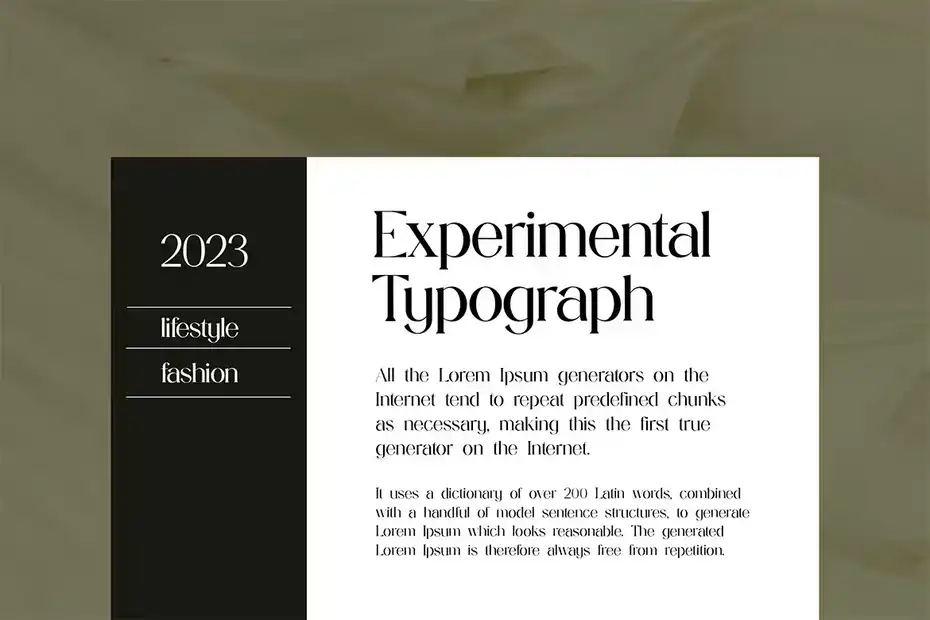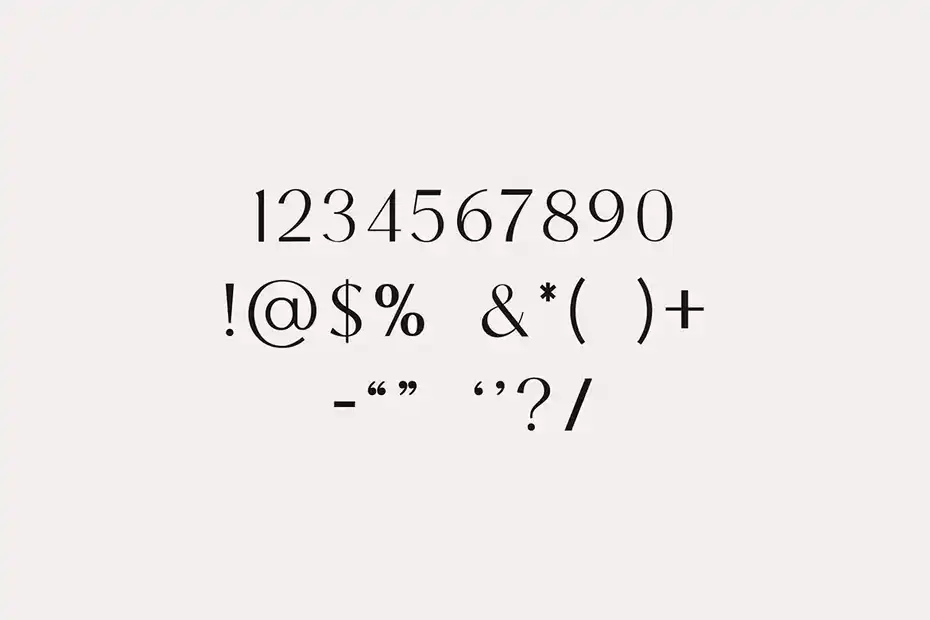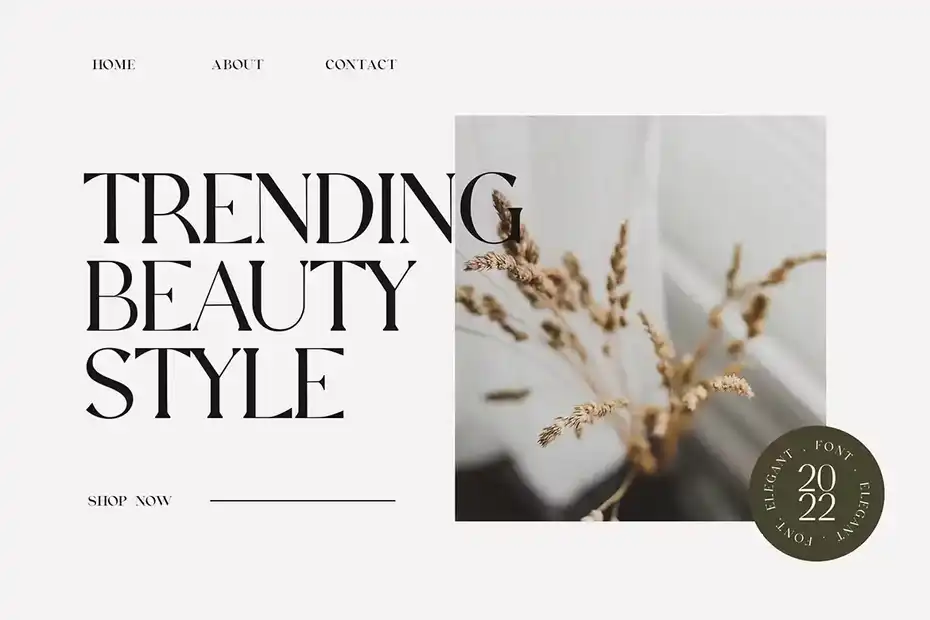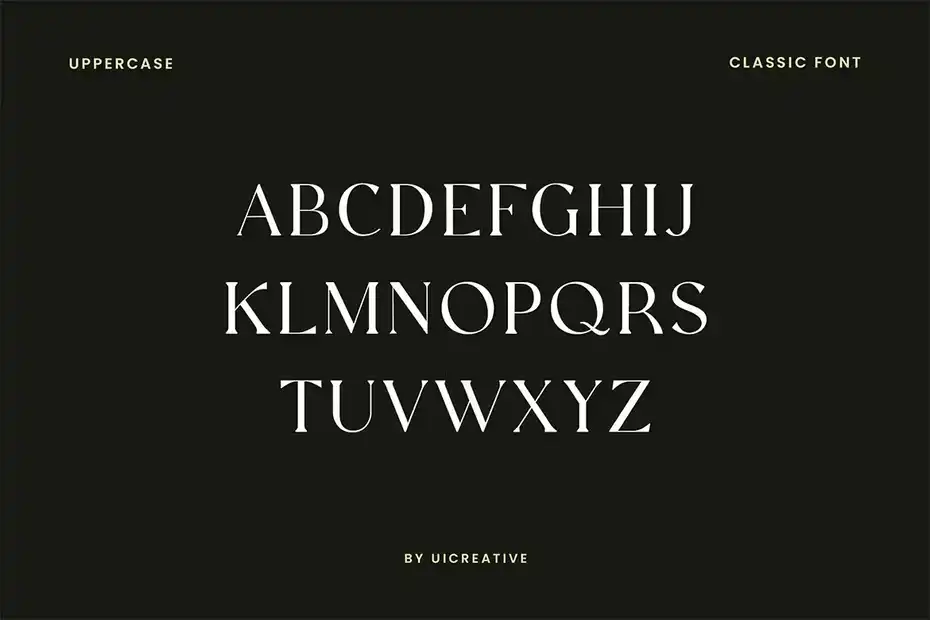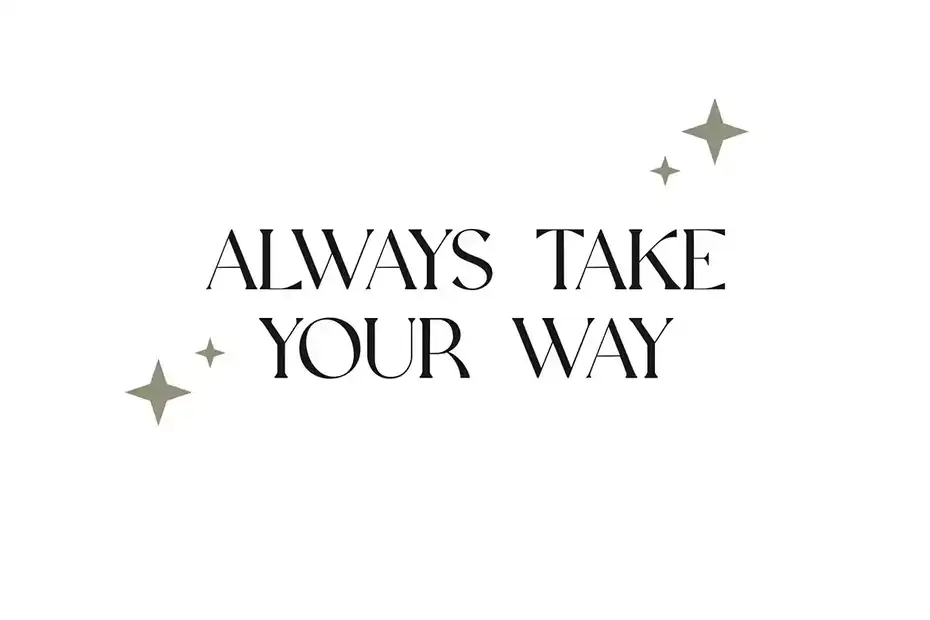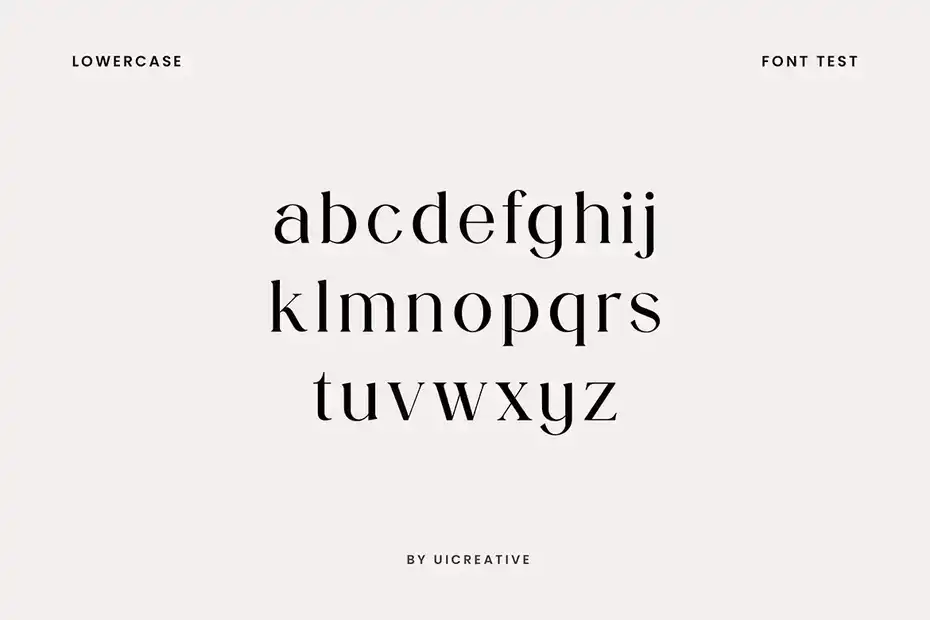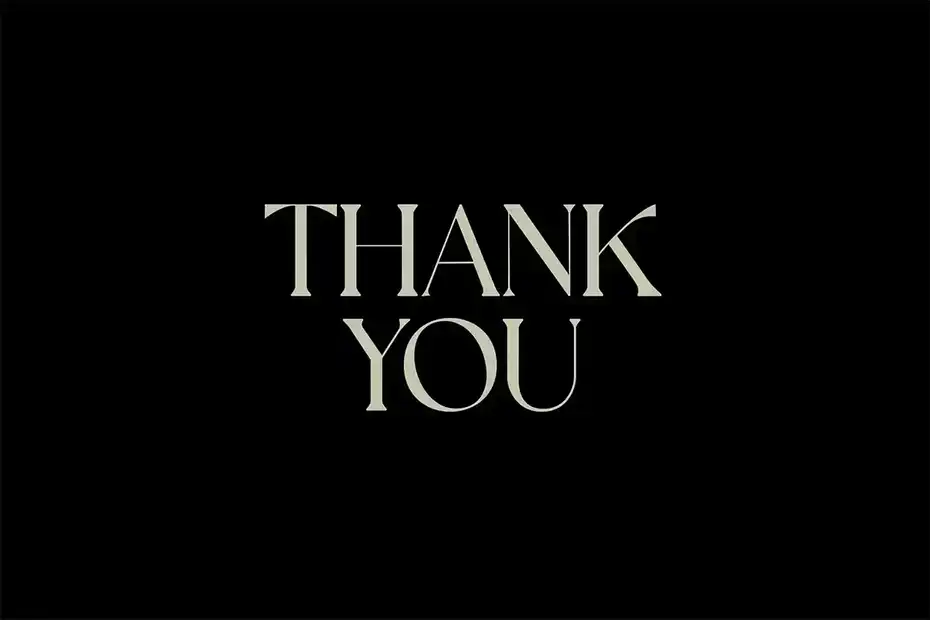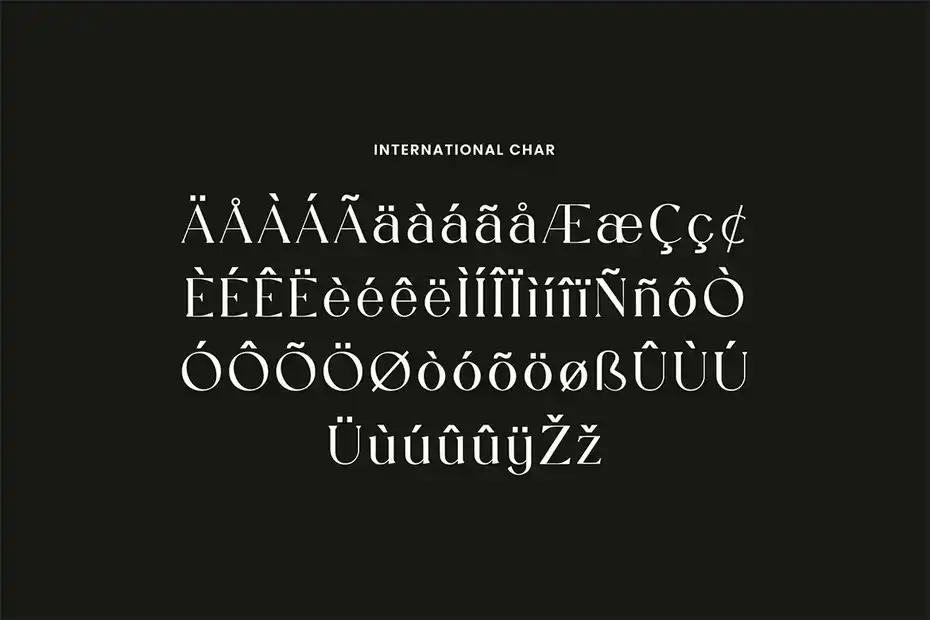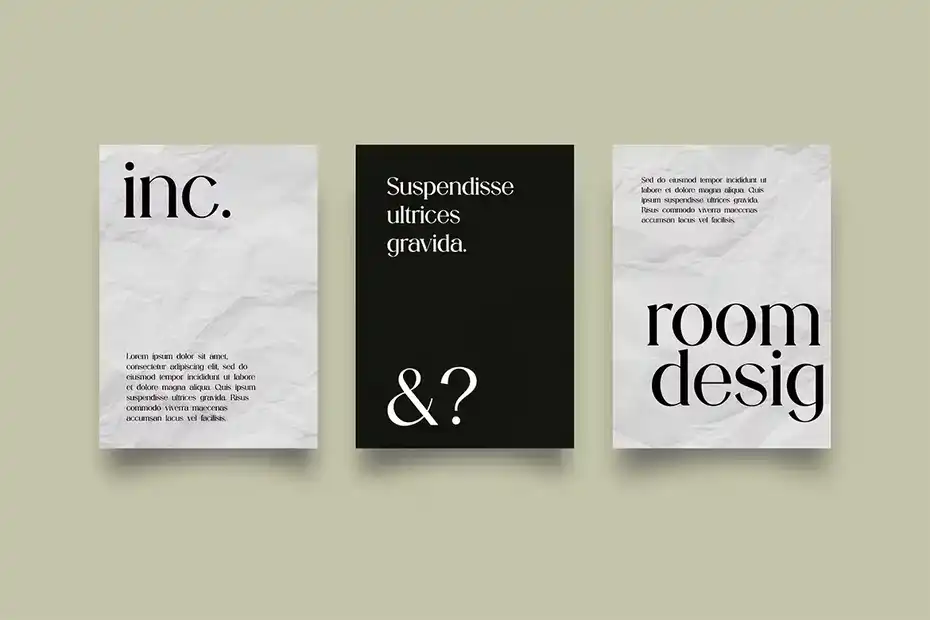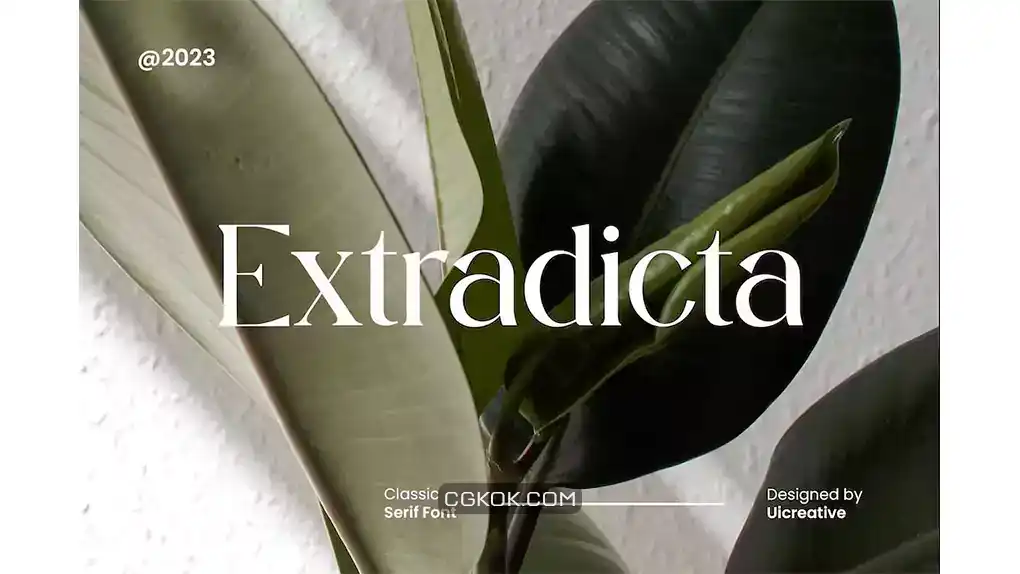
دانلود فونت کلاسیک Extradicta Classic Serif Font
دانلود فونت کلاسیک Extradicta Classic Serif Font : این مجموعه شامل یک فونت انگلیسی کلاسیک است که برای لوگو، برندینگ، امضا، کارت عروسی، تایپوگرافی، جلد مجلات و کتاب، وب سایت، بسته بندی و غیره مناسب میباشد. برای مشاهده موارد مشابه بیشتر حتما بخش دانلود فونت انگلیسی کلاسیک را در سیجی کوک بررسی کنید.
• عنوان مجموعه: Extradicta Classic Serif Font
• سبک: Serif